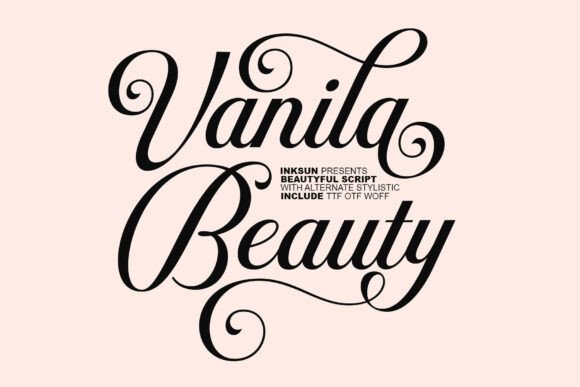
Vanila Beauty
適切なデザイン要素を見つけるのは難しい場合がありますが、Vanila Beautyは作品を即座に引き立てる優れたコレクションを提供します。
POD(オンデマンド印刷)製品、結婚式の招待状、またはソーシャルメディアのグラフィックを作成している場合でも、Vanila Beautyは理想的です。